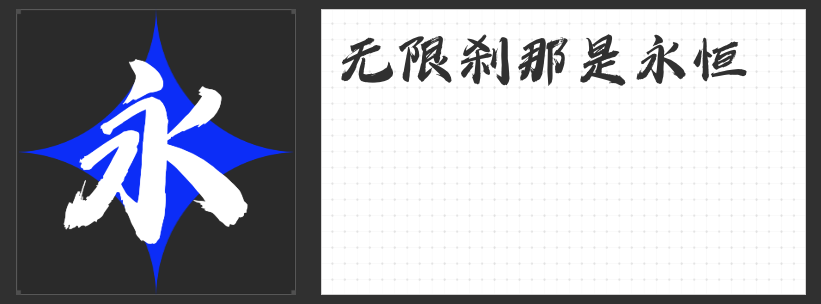
国潮设计字体推荐:四款力作诠释东方美学新风尚
国潮设计的核心在于传统与现代的碰撞,而字体的选择直接影响视觉表达的张力。以下四款专为国潮场景打造的字体,以独特的笔触、结构与气韵,为品牌注入文化灵魂与视觉冲击力。
一、造字侠伏魔简繁 传神
这款字体以“力透纸背”的笔墨质感为核心,粗细对比强烈却不失平衡,中正的字体结构暗藏收放自如的巧思。其笔画设计极具戏剧性——“勾、提、挑、捺”等细节被夸张化处理,如利刃出鞘般锋芒毕露,单字即可成为视觉焦点。无论是作为标题的点睛之笔,还是作为品牌符号的延伸,其强烈的视觉冲击力都能瞬间传递国潮的硬核态度。
二、造字侠永刚漆书简繁
灵感源自传统漆书工艺,这款字体以毛笔手书的自然肌理为基底,笔画厚重如金石镌刻,撇捺间却透出从容灵性。框架醒目而不呆板,字形端庄中暗藏变化,整体风格统一却富有层次感。其适用性极广:包装印刷中可凸显产品质感,广告设计中能强化品牌记忆点,平面布局中更能以“留白与厚重”的对比营造高级感。
三、造字侠侠义简繁
以“潇洒狂放”为灵魂,这款字体突破传统楷书的规整,以圆转笔画替代方折,点画间通过勾挑牵丝强化呼应,如行云流水般一气呵成。其端正平稳的骨架与放纵流动的细节形成微妙平衡,既保留了书法的写意之美,又赋予设计大气磅礴的视觉张力。适用于需要传递文化厚度与个性态度的场景,如国潮服饰、文创产品等。
四、高手兵克逍遥体
字形取法古意,笔画却充满现代设计感——收笔处如刀削般利落,转折处暗藏力量感,整体呈现出“潇洒而不羁”的独特气质。这款字体巧妙平衡了传统书法的韵律与当代审美的简洁,既能承载国潮的文化底蕴,又能以鲜明的个性脱颖而出。无论是品牌标语、海报标题还是数字媒体设计,皆能以“收放自如”的笔触传递自由精神。
国潮设计的字体选择,需兼顾文化符号的传承与视觉语言的创新。四款字体以不同的美学路径,为国潮设计提供了丰富的表达维度。选择与品牌气质契合的字体,方能让设计在文化深度与视觉冲击力上实现双重突破。